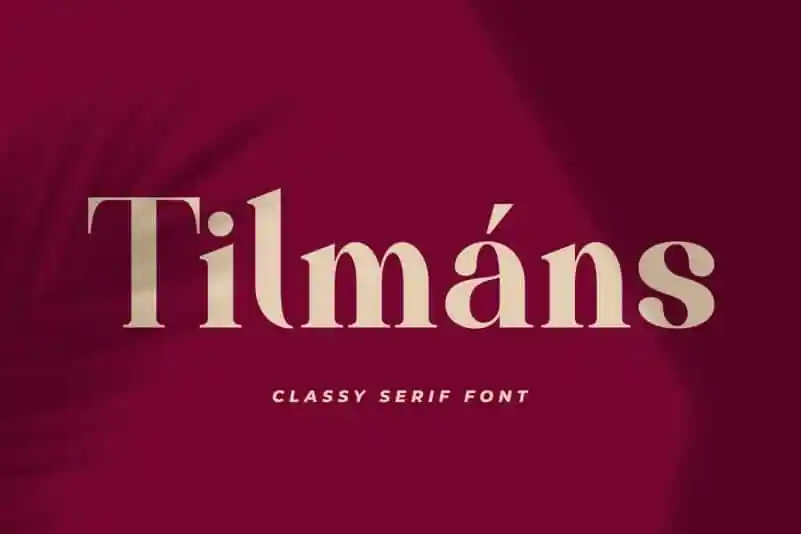
Tilmáns Serif é uma fonte serif inspirada na elegância das serifas clássicas e do estilo tipográfico calligráfico, misturados com um toque moderno. Esta opção de fonte oferece um design contemporâneo e bold, repleto de ligações e alternativas que ajudarão a destacar seu próximo projeto visual ou logomarca. Tilmáns é uma fonte serif multi-idioma compatível com PUA (Predefined Unicode Alternates) encodada, garantindo assim uma variedade incrível de formas para se adaptar aos seus projetos. Como resultado, esta fonte moderna e poderosa será a escolha perfeita para quem busca tanto estética clássica quanto a coragem necessária para destacar em sua apresentação ou logo.